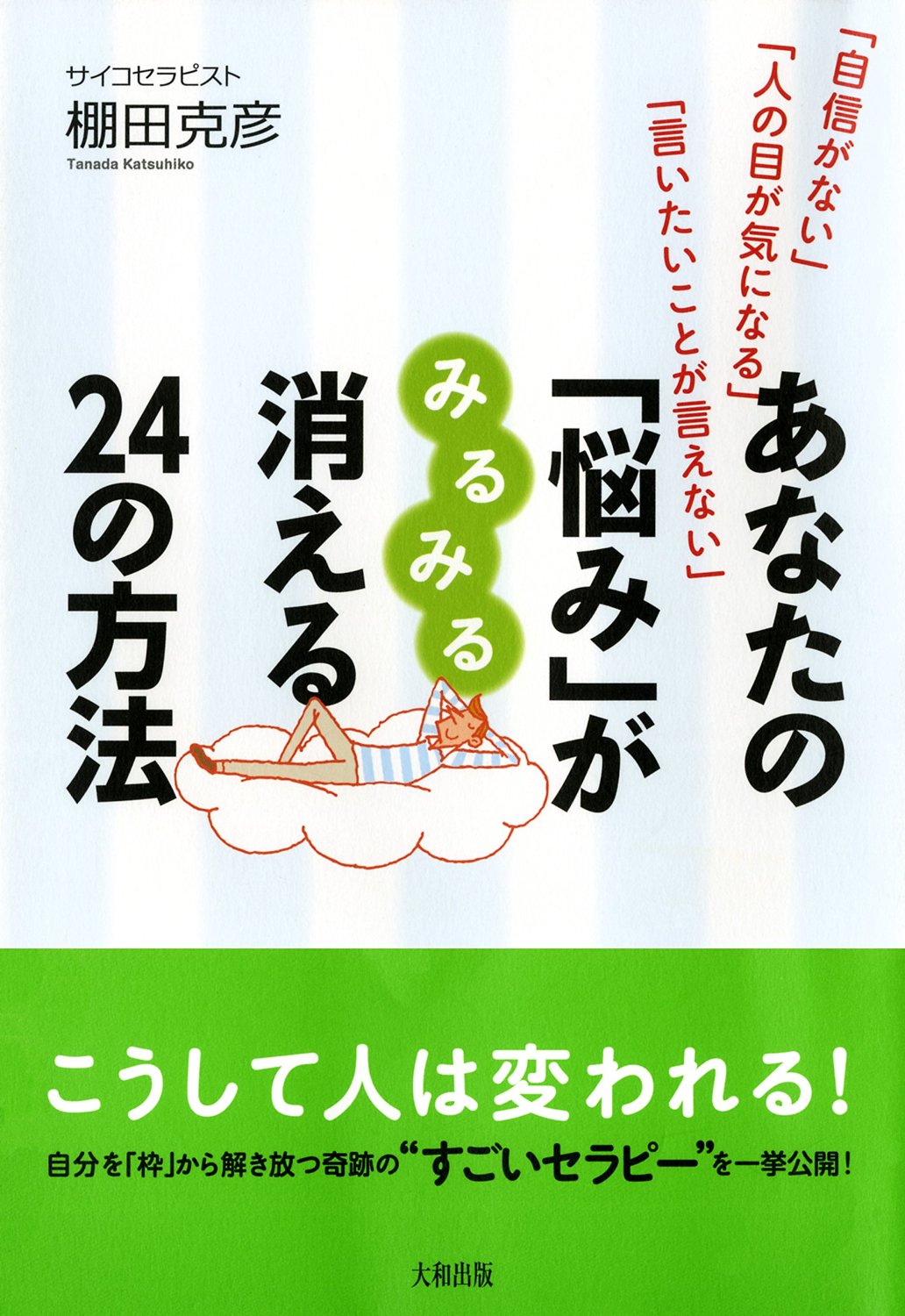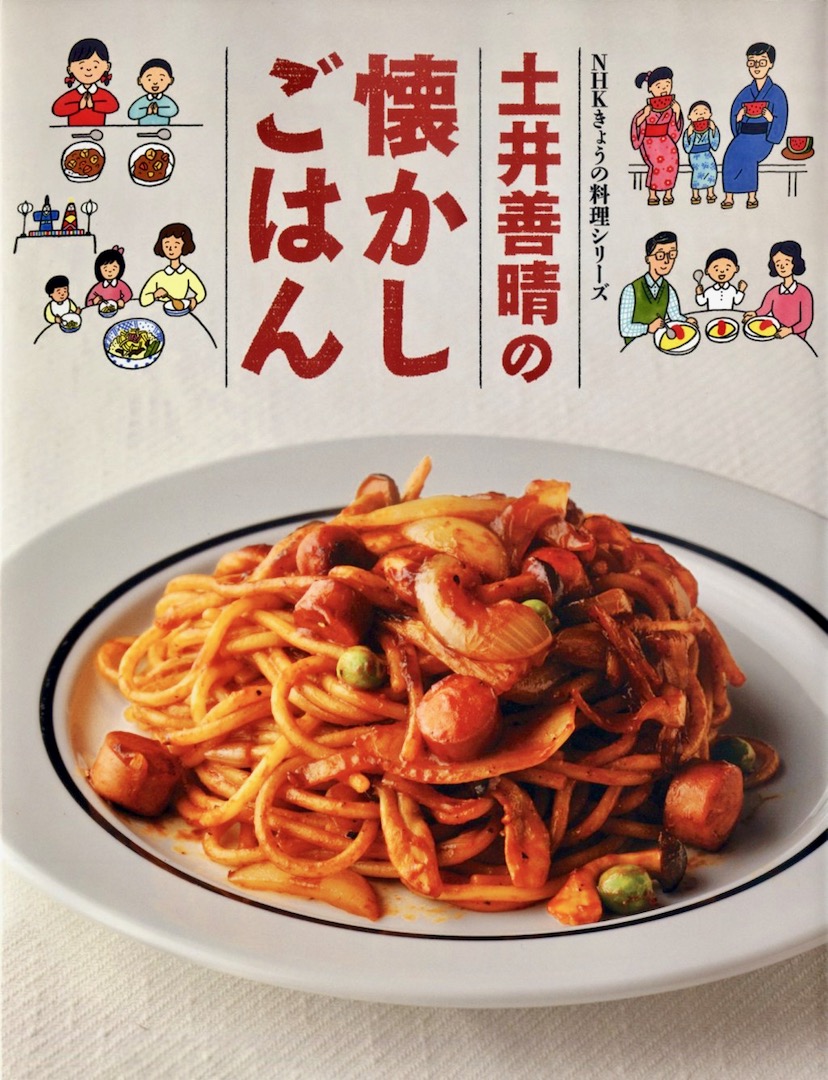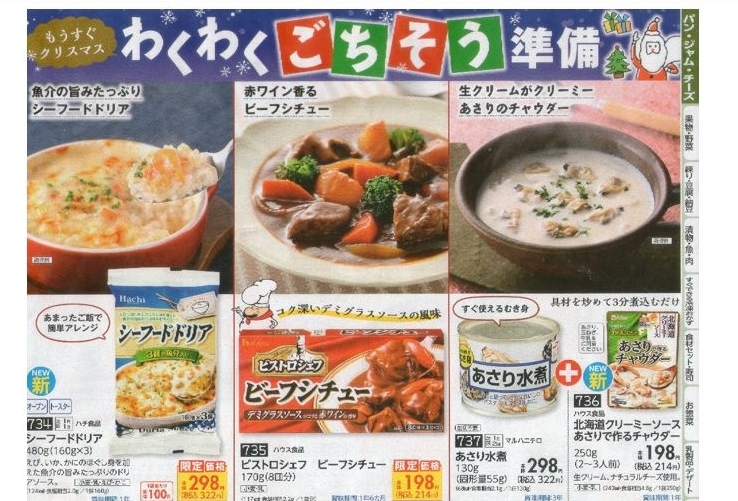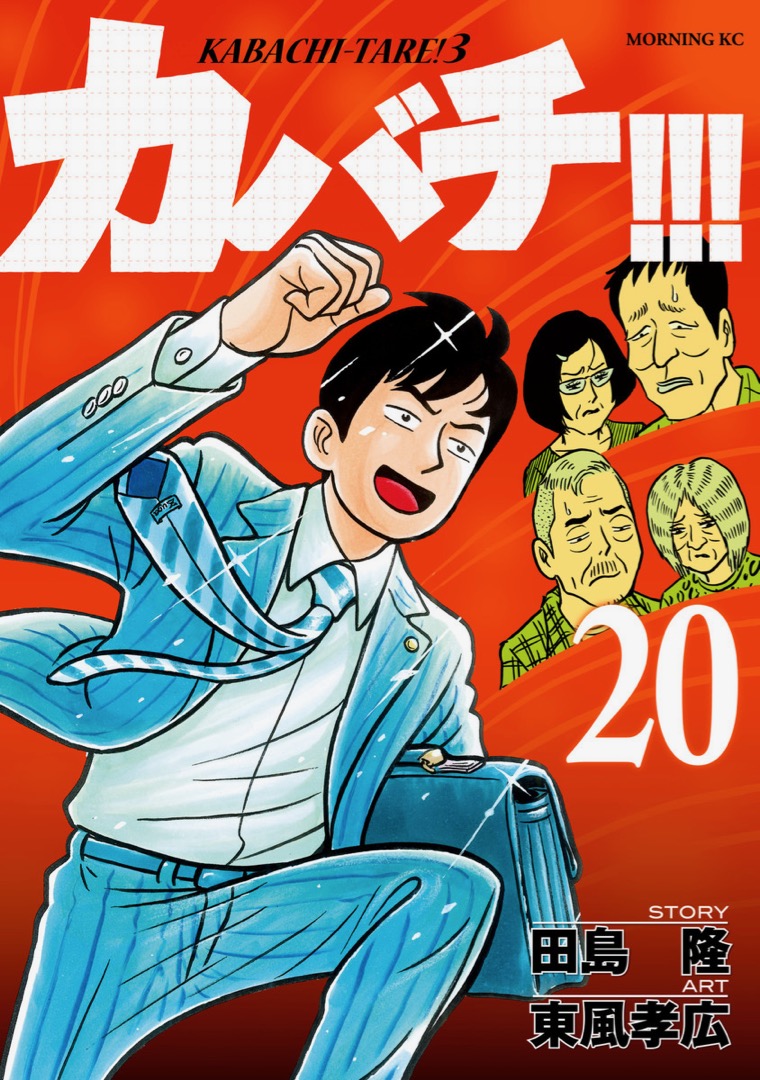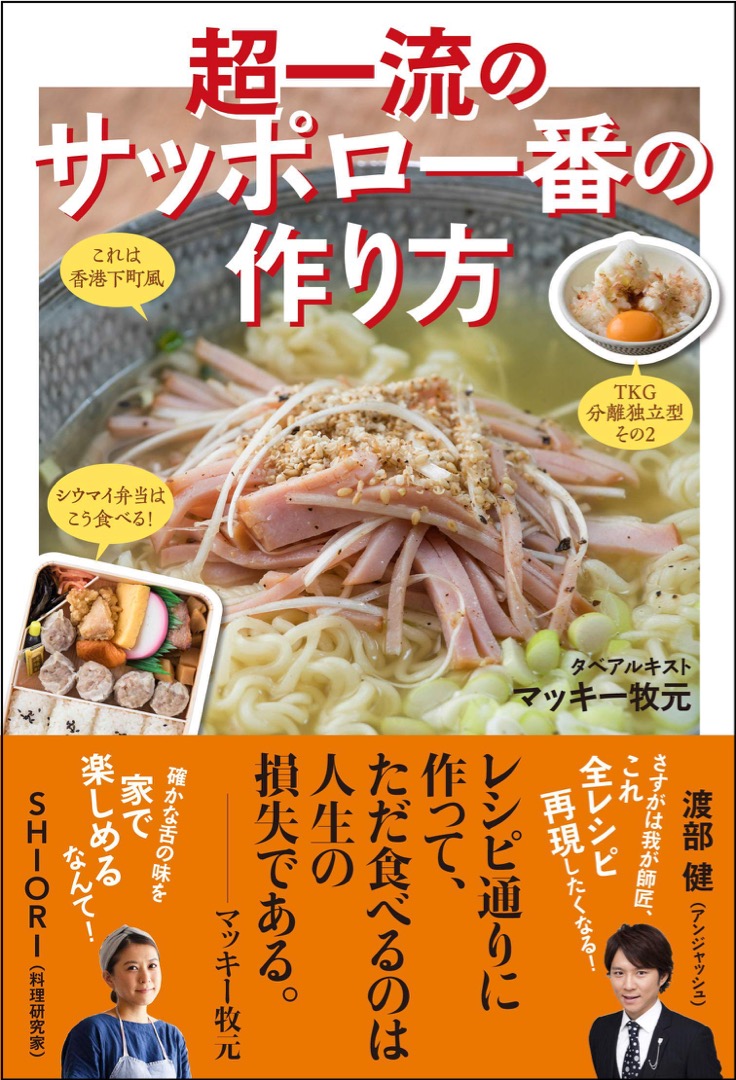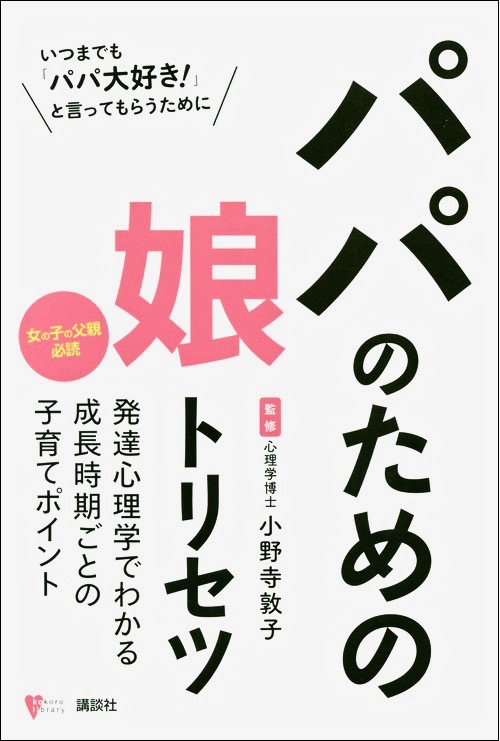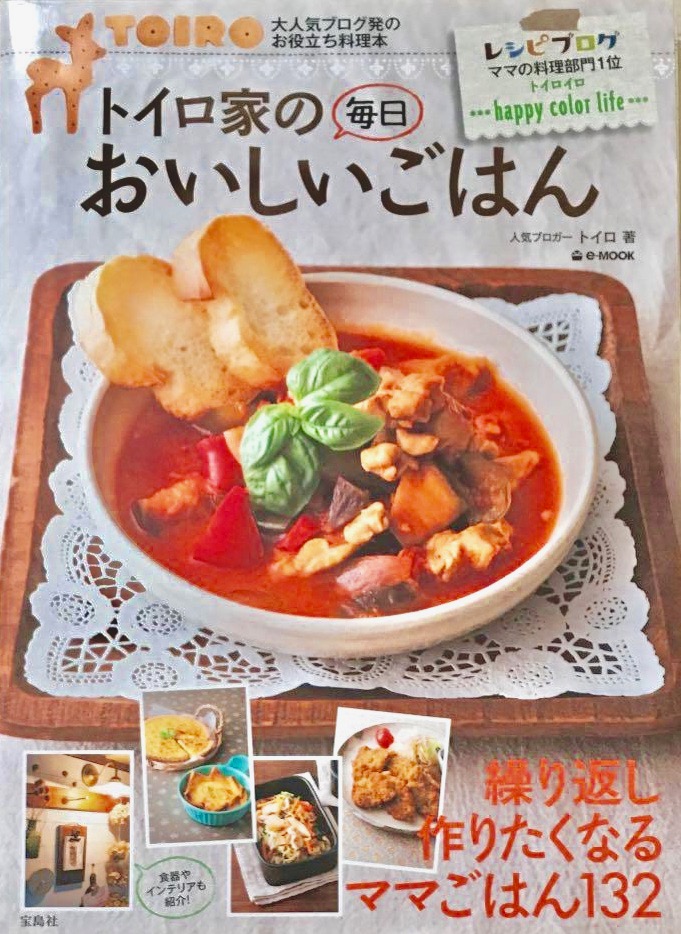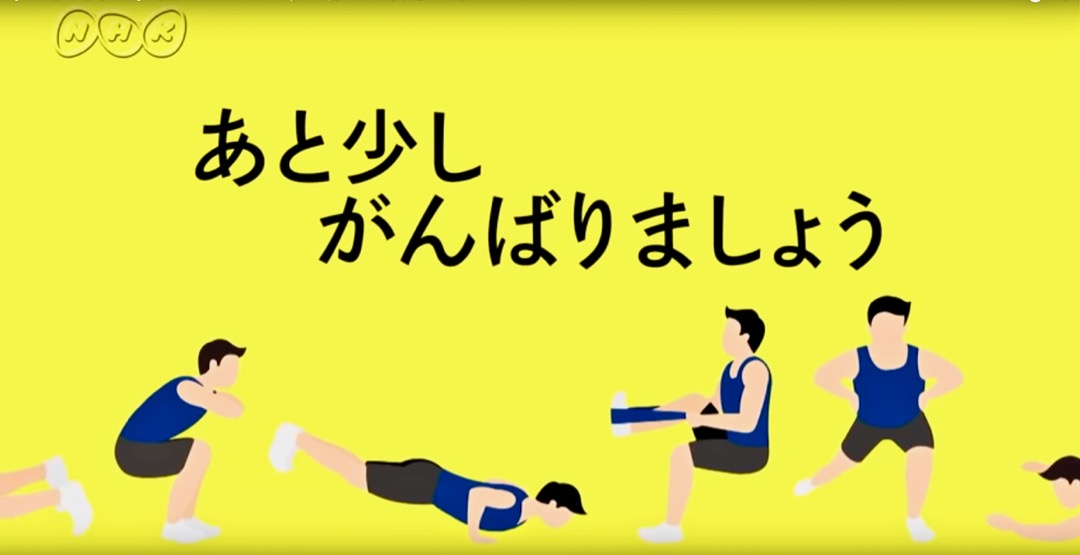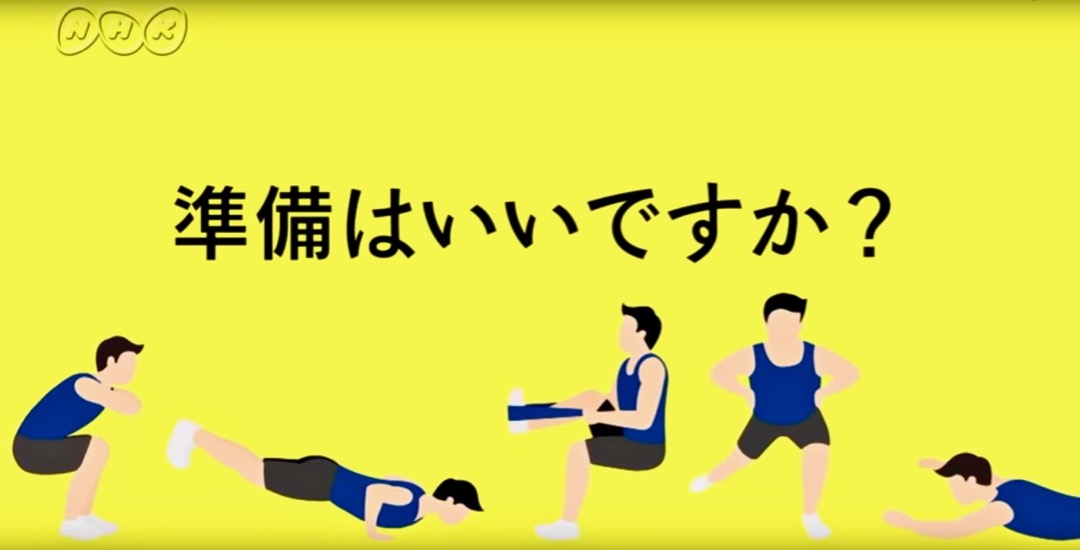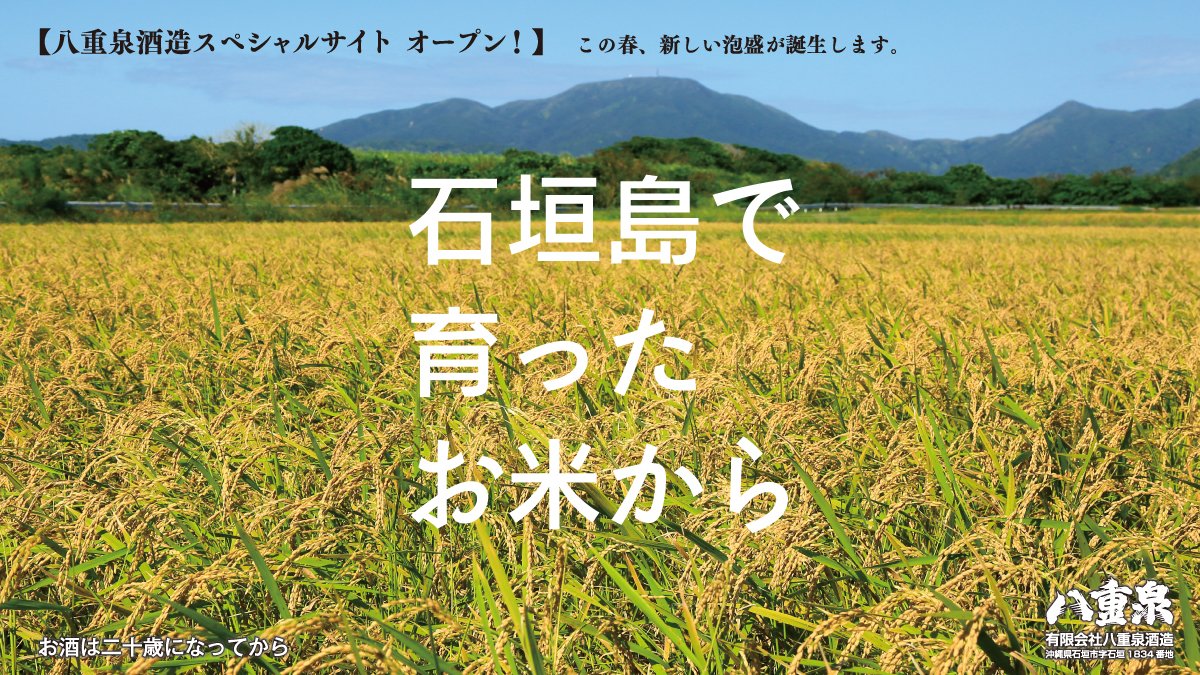
YouTube動画  さとうゆたか  2020年11月4日(水) 16:37
タイプラボのフォントはYouTuberにも好かれているようだ。
動画の中には、ニタラゴフォントが大量に使われている。
付録の冊子  さとうゆたか  2020年10月24日(土) 9:41
新聞の購読者に配布されるもの。
もう1点。
テレビ番組  さとうゆたか  2020年10月4日(日) 15:08
テレビ東京の「大食い女王決定戦2020」。
これも…。
まだある…。
もう1点。
「墨東レラ」のちょっとした発見?  takumi  2020年4月27日(月) 2:55  HP
佐藤さん、こんばんは。
いつもの使用例報告とはちょっと違う発見のレポートです(笑)。
●最近放映されていたリポビタンDのCM
(自粛とかがあって急遽作られたのかも…)
↑この動画で大きく使われているのは他社書体ですが、同じメッセージを「墨東レラ」(いちばん太い6ウェイト)で試してみました。
何の手も加えず、白背景に黒い文字で文字を打ち込んだだけですが、角ゴシック版の「墨東」とは全く異なる印象に感じました。
丸ゴシック(墨東丸)にしたからこその温もりや優しさなどが感じられる一方で、墨東のシッカリした骨格がベースなので、グサッと心に突き刺さる説得力というか、本当に良い意味での、愛情があってこその厳しさみたいなものも持っているような……。
あまり太いのを安易に選んで使うとダサくならないかな?という懸念もありましたが、僕個人的にはそんなに悪くないように感じました。
丸ゴシックになるだけで、こんなにも印象が変わって見えるのだな、と感動したので、ここに投稿させて頂きました。
もちろん、選ぶウェイトとか、組み方とか細かいテクニックなど、使い手の工夫次第でまたいろいろな印象が生まれるのだと思いますが、ひとつの発見として、ここに残しておきますね。
<追記>
もう1枚。
これは、従来(角ゴシック版)の「墨東ルイカ」(06ウェイト)です。
これはこれで大いにアリですが、やはり丸ゴシックの「墨東レラ」とは全くと言って良いくらい印象が違いますね。
さとうゆたか  2020年4月27日(月) 8:59 [修正]
墨東レラの試し組、作っていただき感謝いたします。
私自身、最近はメールを読むのに使ってるんですが、なかなかいい感じです。
将来は、タイプラボサイト内も墨東レラに表示設定するか? なんて考えたりして…います。
雑誌の表紙  さとうゆたか  2020年4月22日(水) 9:14
この雑誌のロゴになっているから毎年のことだけど…。
書名:このミステリーがすごい!(2020年版)
発行:宝島社
墨東を丸ゴに  さとうゆたか  2020年4月12日(日) 11:44
かな書体「墨東」を丸ゴシック化した「墨東丸」を作りました。
丸ゴシック「レラ」と組み合わせて総合フォントにする予定です。
さとうゆたか  2020年4月14日(火) 9:26 [修正]
これが昨日頒布開始した、レラと組み合わせた「墨東レラ」です。
PR誌  さとうゆたか  2020年3月25日(水) 16:25
新聞社が購読者に配布している物。
表紙や本文ページの見出しに使われていた。
本文ページ。
これも…。
本の表紙  さとうゆたか  2020年3月12日(木) 16:23
書名:ダウン症の子どもたち
著者:稲沢潤子、オノビン
発行:大月書店
テレビ番組  さとうゆたか  2020年2月15日(土) 10:00
テレビ東京「最強大食い王決定戦2020」。
もう1点。
これも…。
ジェンダーフリー絵本  さとうゆたか  2020年2月4日(火) 9:18
書名:こんなのへんかな?
著者: 橋本紀子、朴木佳緒留
発行:大月書店
さとうゆたか  2020年2月4日(火) 9:19 [修正]
これも…。
さとうゆたか  2020年2月4日(火) 9:20 [修正]
もうひとつ。